フォントを作る人に聞いてみた その2:好きな漢字グリフ3
タイププロジェクトのスタッフ達に「好きな漢字グリフ」は何かを聞いてみました。
これまでの2記事では部首や構成など複数のグリフをまとめて回答しているものを多く紹介しましたが、今回の記事では1つのグリフを挙げているものを紹介します。
- 脩:
好きなというのとはちょっと違うかもしれませんが、この道に進む後押しをしてくれた恩師の名前です。
- 矢:
一番馴染み深いものだから
- CID+7710:
一時期写研の文字盤では「靱」のデフォルトがこれだったと思いますが、今ではもうほとんど目にすることはありません。
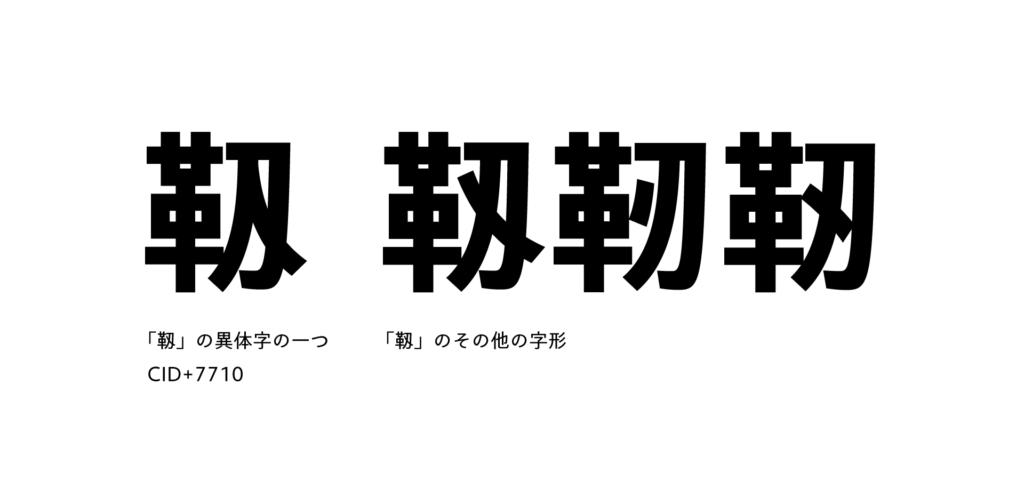
これらのように、ゆかりのある人の名前に使われているもの、以前よく使用されていたけれど今では見かけないものなどそれぞれに思い入れがあるグリフについての回答も複数ありました。